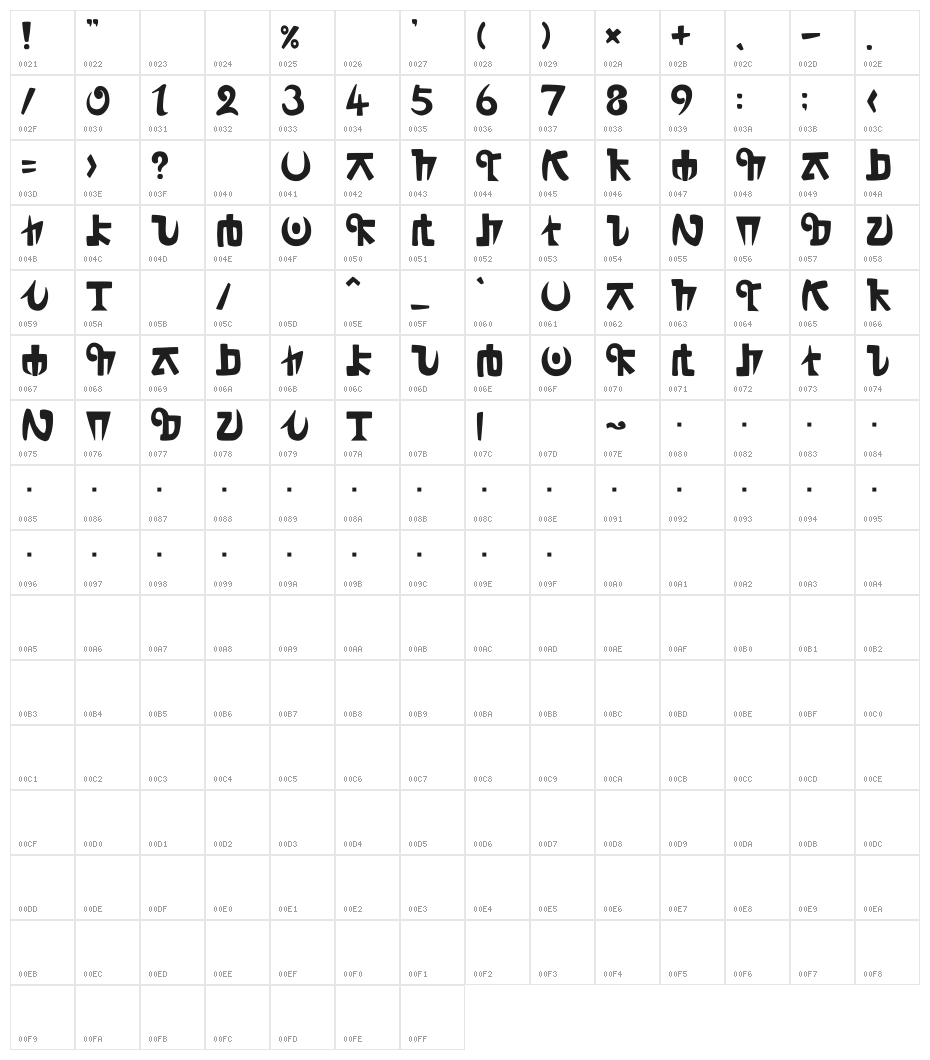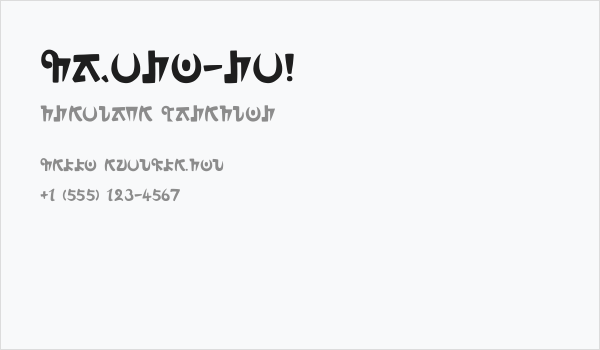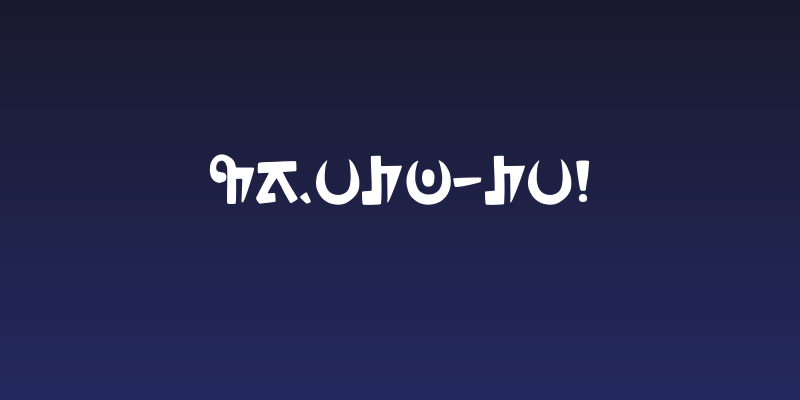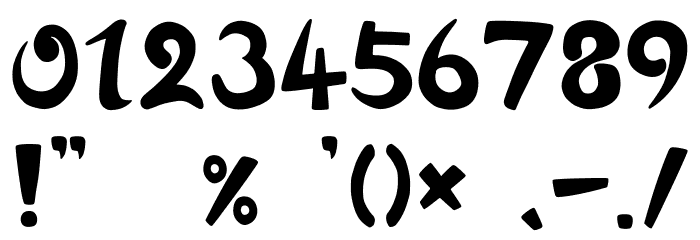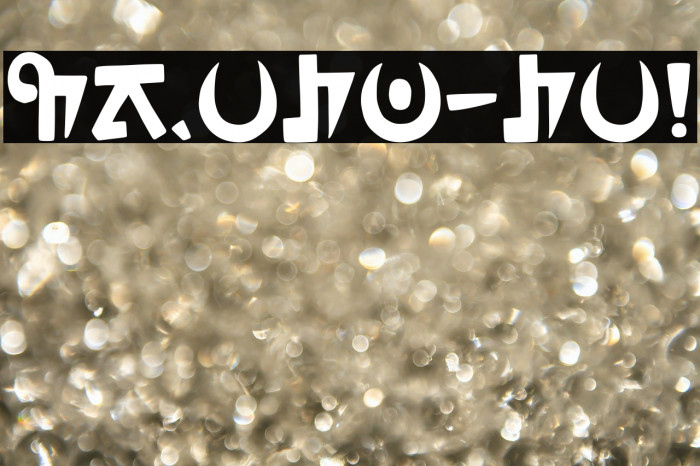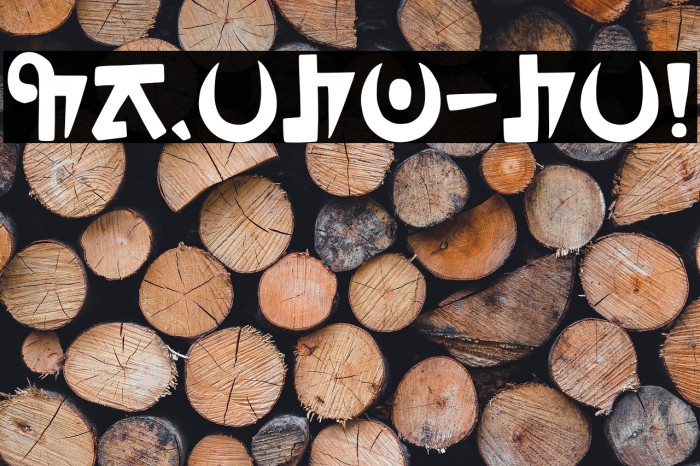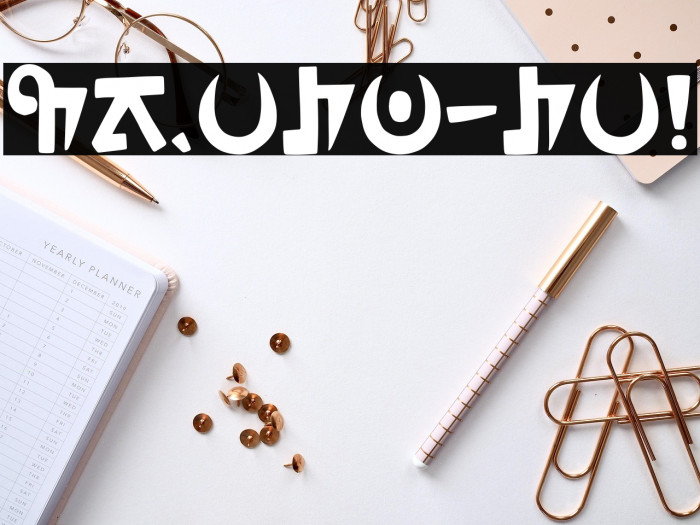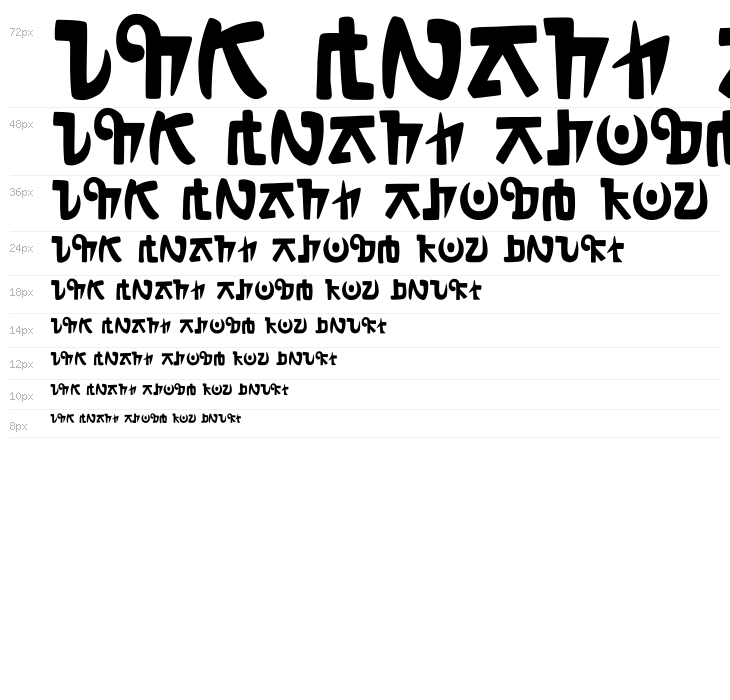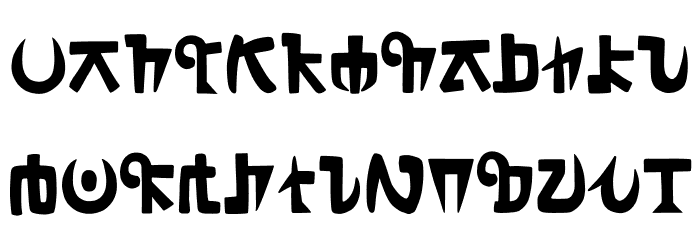
Hi,Aro-ra! Font
| 全体的なスタイル | Playful, Whimsical, Creative |
| 用途 | Headlines, Posters, Creative Designs |
| おすすめプロジェクト | Great for children's books, playful branding, posters, and creative design projects. |